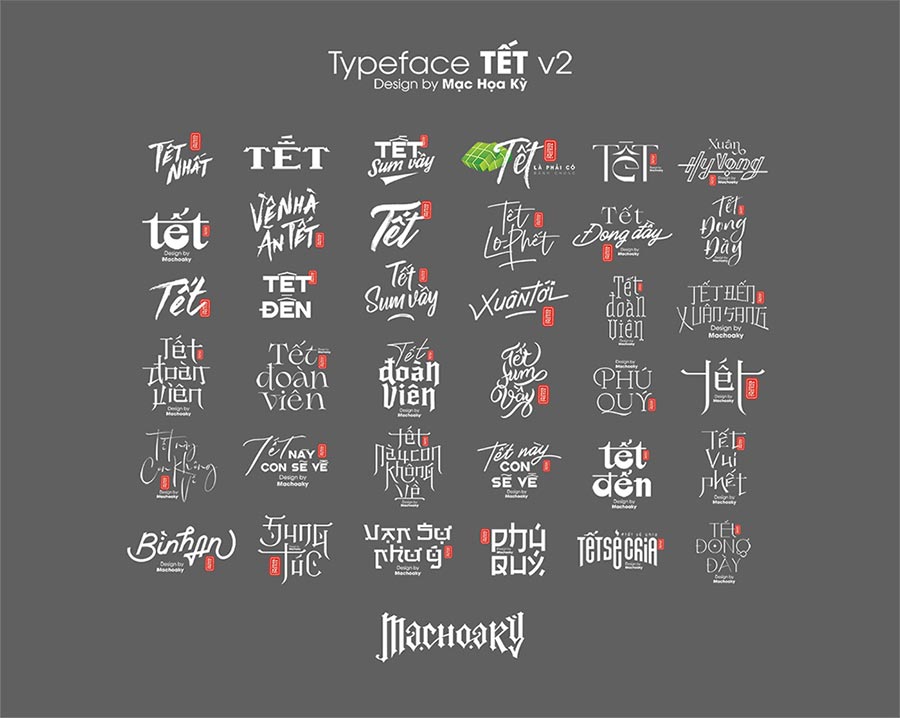
Chia Sẻ Miễn Phí Typeface Tết V2 By Machoaky CV
Typography luôn là một yếu tố quan trọng trong thiết kế đồ họa, đặc biệt khi cần truyền tải những giá trị văn hóa và cảm xúc đặc trưng. Với dịp Tết Nguyên Đán – một trong những sự kiện lớn và ý nghĩa nhất trong năm của người Việt, việc sử dụng các typeface mang đậm dấu ấn truyền thống là một cách tuyệt vời để tạo nên các sản phẩm thiết kế ấn tượng. Hiểu được nhu cầu này, sadesign.vn đã chia sẻ miễn phí bộ Typeface Tết V2 do Machoaky thiết kế, mang đến cho cộng đồng sáng tạo một công cụ hữu ích và đầy cảm hứng.
Điểm Nổi Bật Của Typeface Tết V2
Typeface Tết V2 không chỉ đơn thuần là một bộ font chữ mà còn là một tác phẩm nghệ thuật, được thiết kế tỉ mỉ để tái hiện lại nét đặc trưng của văn hóa Việt Nam trong dịp lễ Tết. Một số điểm nổi bật của bộ typeface này bao gồm:
1. Phong Cách Thiết Kế Độc Đáo
Typeface được lấy cảm hứng từ các yếu tố truyền thống như thư pháp, họa tiết dân gian và màu sắc đặc trưng của ngày Tết. Điều này giúp người dùng dễ dàng áp dụng vào các thiết kế như thiệp chúc Tết, bao lì xì hay poster sự kiện.
2. Tính Ứng Dụng Cao
Bộ font này phù hợp cho nhiều loại dự án khác nhau, từ thiết kế đồ họa, in ấn đến nội dung số. Với khả năng hỗ trợ tiếng Việt đầy đủ, Typeface Tết V2 là lựa chọn lý tưởng cho các nhà thiết kế trong nước.
Sự đóng góp của Machoaky – nhà thiết kế đứng sau Typeface Tết V2 – là một minh chứng rõ ràng cho tinh thần sáng tạo và sẻ chia trong cộng đồng thiết kế Việt Nam. Những sản phẩm như thế này không chỉ giúp nâng cao chất lượng các dự án thiết kế mà còn góp phần quảng bá văn hóa Việt ra thế giới.
Typeface Tết V2 không chỉ là một bộ font chữ mà còn là cầu nối giữa nghệ thuật thiết kế hiện đại và giá trị truyền thống. Nếu bạn đang tìm kiếm một giải pháp sáng tạo cho các dự án liên quan đến dịp Tết, đây chắc chắn là lựa chọn không thể bỏ qua. Hãy tận dụng cơ hội này để mang đến những sản phẩm thiết kế đậm chất Việt Nam và lan tỏa giá trị văn hóa dân tộc.